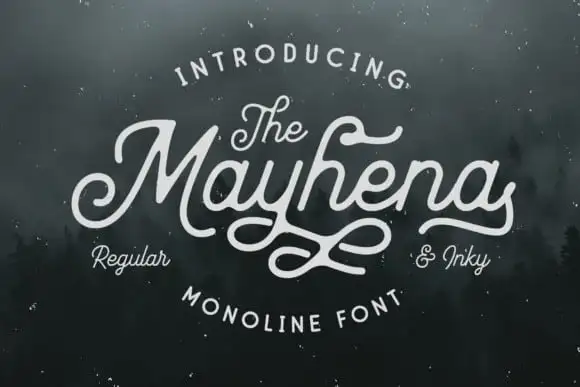
Mayhena Inky Script Font
Descubra uma nova adição ao seu arsenal de fontes: Mayhena Inky Script Font. Esta fonte tipográfica conectada tem um estilo vintage e é perfeita para dar vida a seus projetos. Arterfak Project é o criador da font, trazendo uma variedade impressionante de alternativas de caracteres decorativos que permitem maior flexibilidade ao criar designs. Os usuários podem escolher entre diferentes caracteres para personalizar cada palavra em seu projeto, dando um tom único e impecável à tipografia. A fonte está disponível nas versões Regular e Inky, proporcionando uma gama de possibilidades design para seus trabalhos. Se você é apaixonado por estilos elegantes e vintage, esta é uma fonte que não pode ficar fora de seu radar.